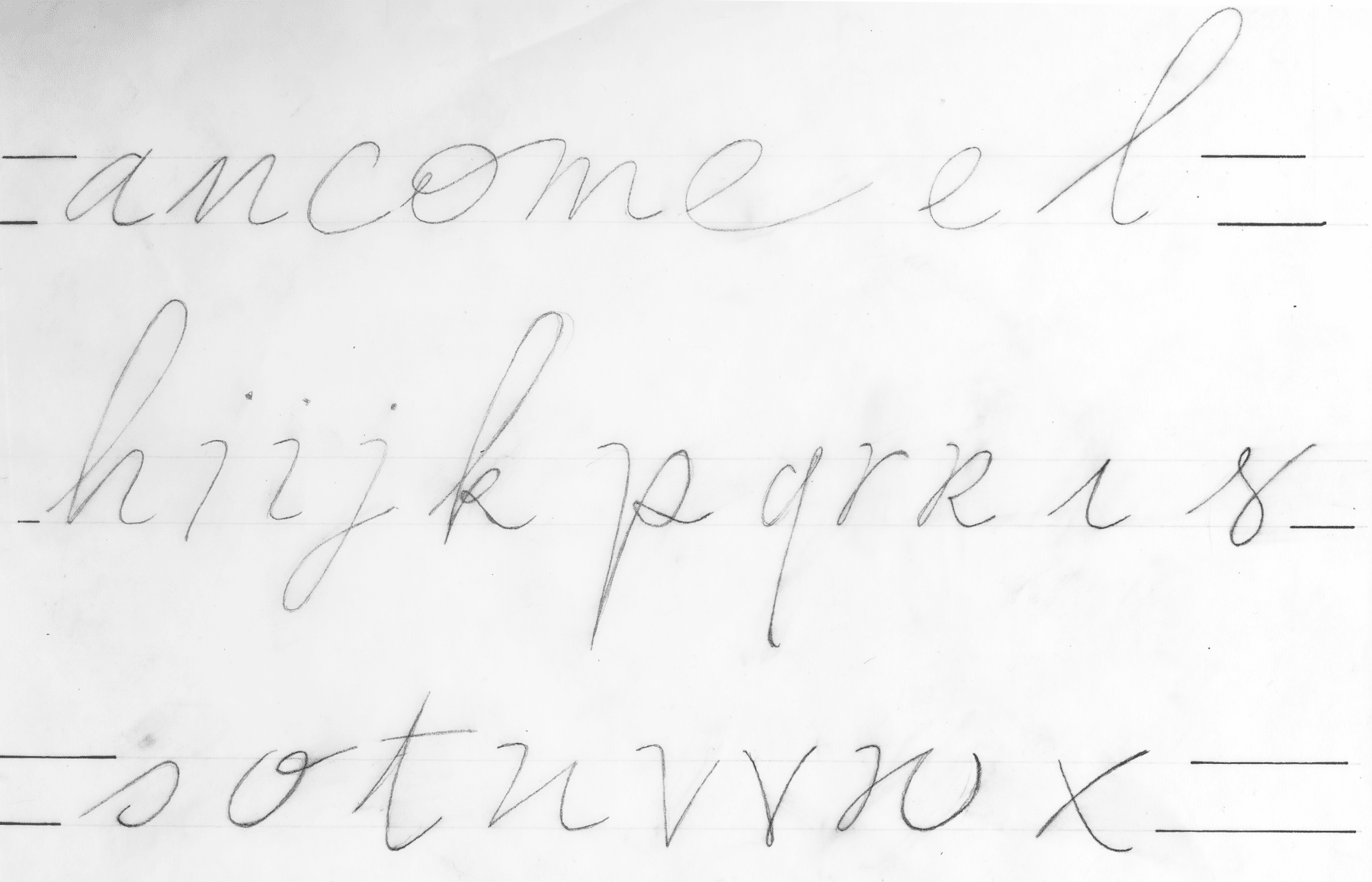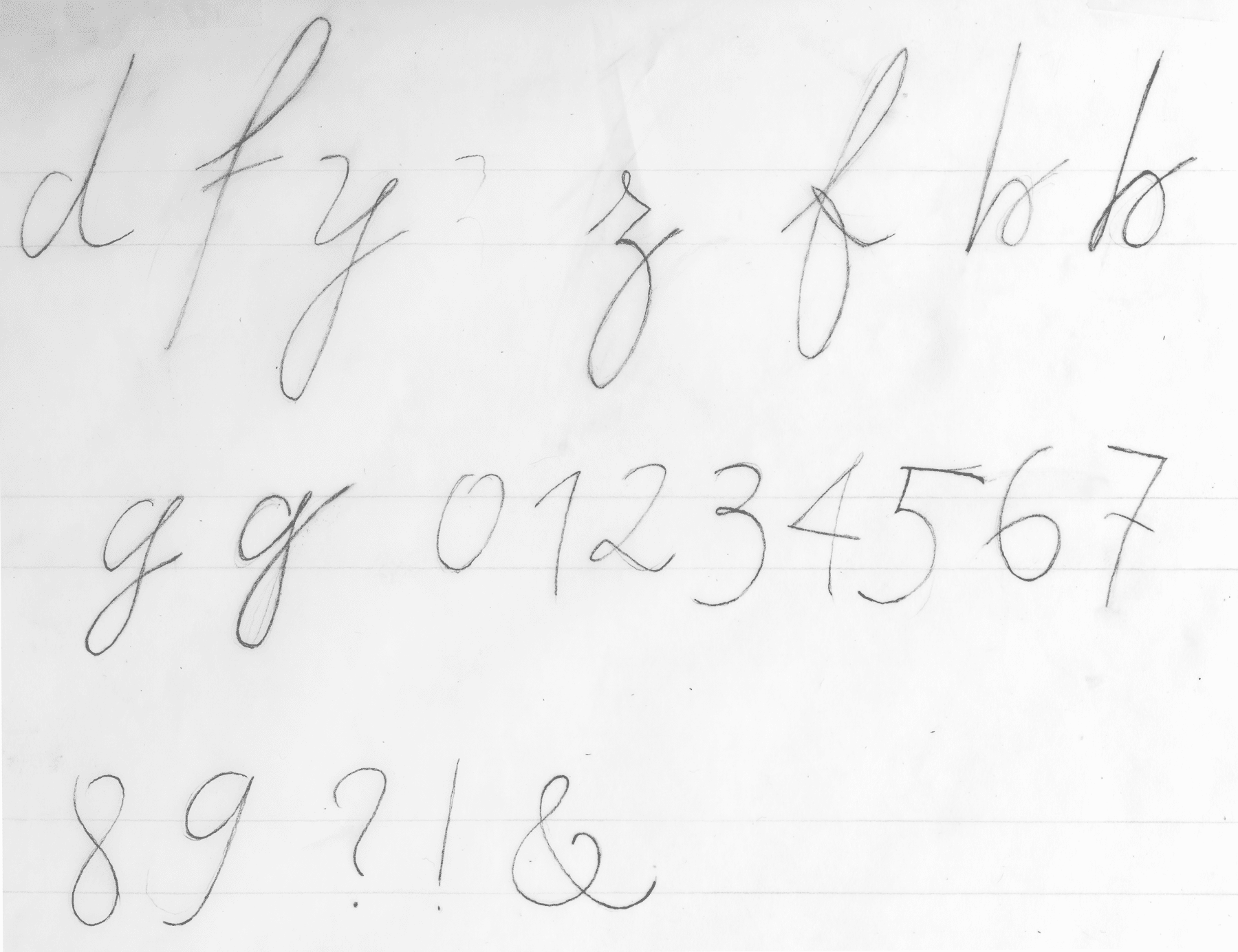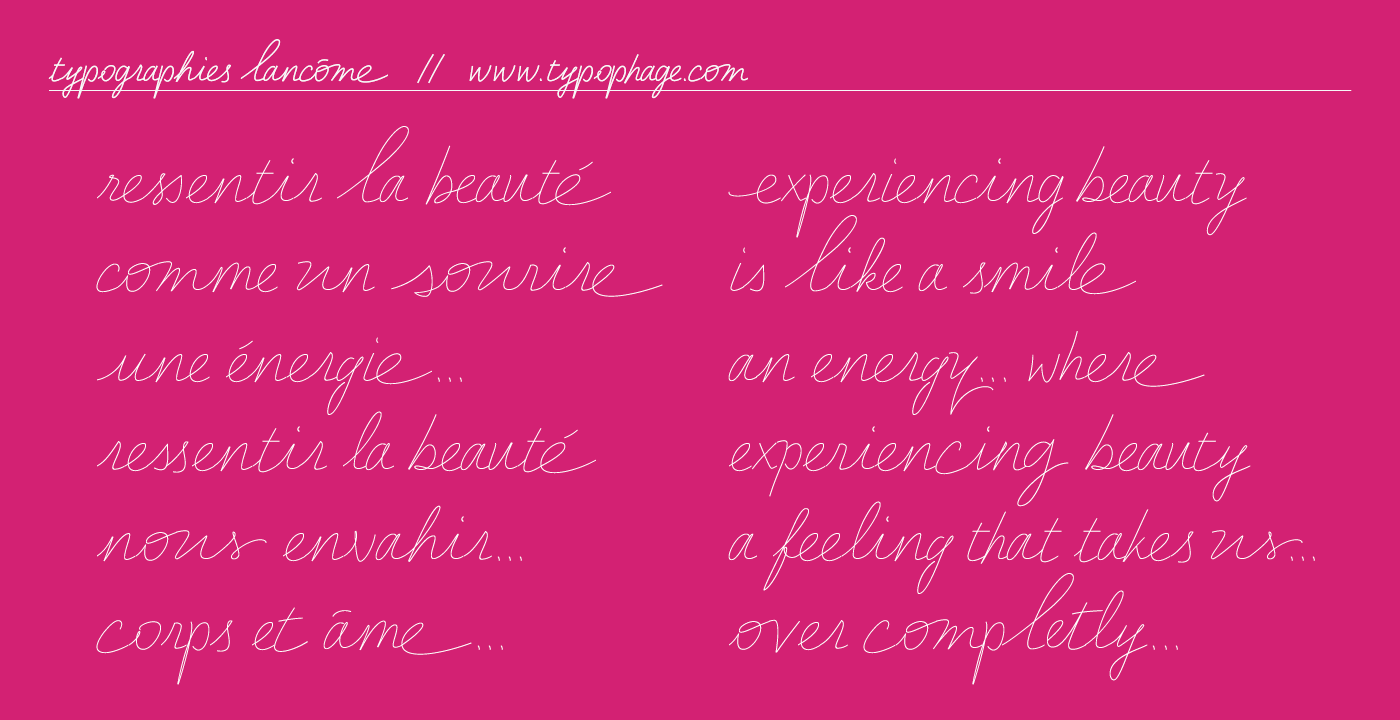
Lancôme
Typographie scripte
La typographie Lancôme a été dessinée pour la maison de cosmétiques et de produits de luxe, commanditée et en collaboration avec l’agence Publicis 133.
Trois styles ont été développés : Lancôme Extra Light, Lancôme Extra Light Alternate et Lancôme Light.
La version Extra Light est la base. L’alphabet tout en minuscules a été dessiné sur calque puis numérisé.
Cette écriture évoque la légèreté et la féminité.
Un second alphabet de minuscules remplace les majuscules, ce qui permet d’utiliser 2 versions dans une même fonte.
La version Extra Light Alternate comporte des caractères différents, avec des ligatures, lettres de début ou fin de mot pour obtenir une écriture plus naturelle.
La version Light est légèrement plus épaisse pour les textes en petites tailles.
Typographie Lancôme, les trois styles.
Typographie Lancôme
Dessins sur calques